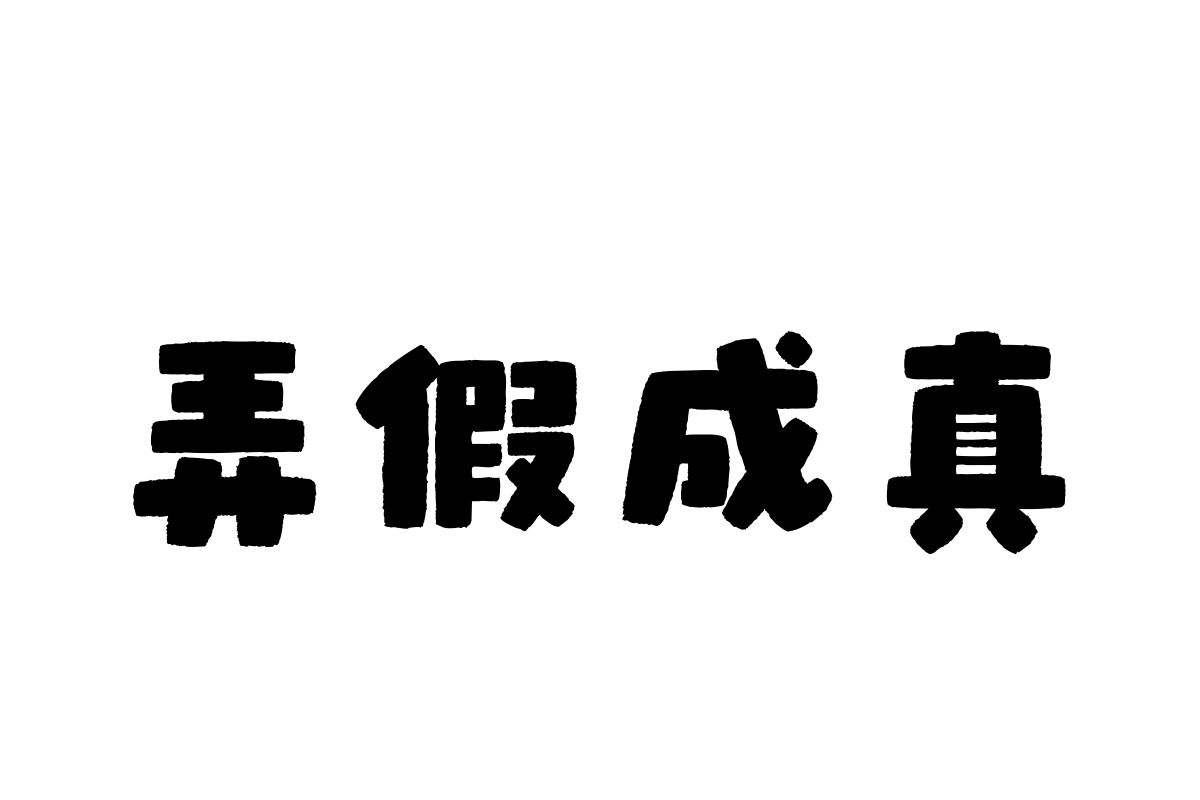
汉仪布袋熊基础款繁体字体是一款非常实用且美观的字体。这款字体具有独特的设计,使得它在视觉上呈现出一种简约而不失优雅的风格。它的字形结构清晰,笔画流畅,给人一种舒适的感觉。
此外,汉仪布袋熊基础款繁体字体还具有良好的可读性,无论是在印刷还是在其他媒介上,都能清晰地显示文字内容。这使得它成为了设计师们的首选字体之一。
总的来说,汉仪布袋熊基础款繁体字体是一款非常适合用于各种场合的字体,无论是用于网页设计、平面设计还是其他任何需要文字的地方,它都能展现出其独特的魅力。